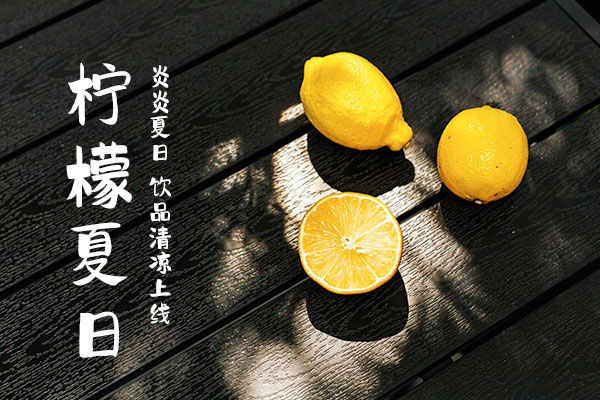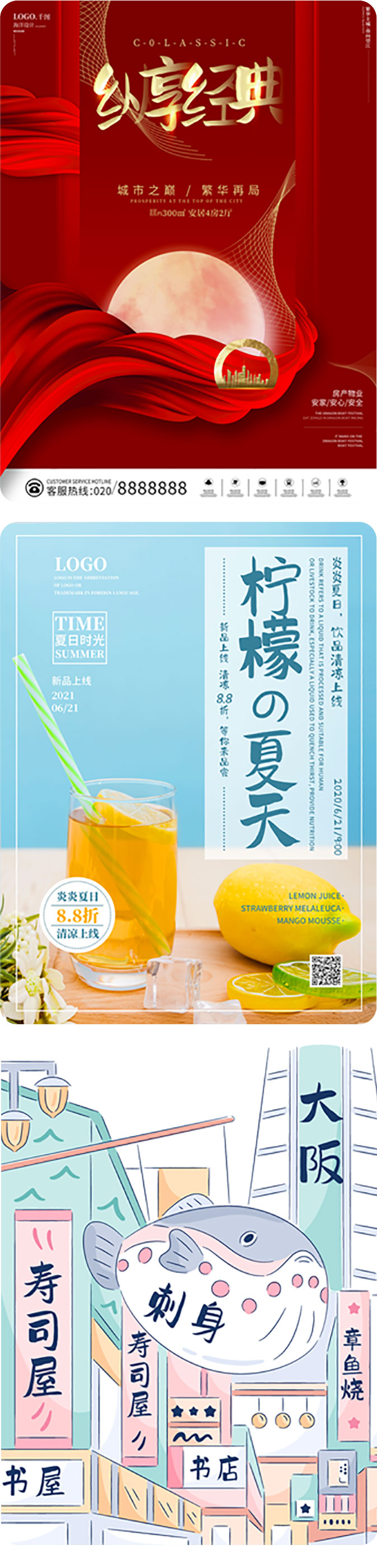
千图马克手写体
千图马克手写体,一款由千图网精心打造的免费商用字体,它的独特风格给人带来一种积极、阳光的感觉。字体设计中,注重笔画的开合度,每个字形之间都保持了恰当的空间,使得文本的排列通透,阅读起来更为轻松、舒适,宛如自由呼吸。
这款字体非常实用,既适合作为标题使用,也可以用于提醒类文字,可以广泛应用于各种场景。无论是在饮品、化妆品、日料、插画等领域,都能发挥出其独特的魅力。
千图马克手写体是由千图网联合国内专业字体设计机构字魂网精心打造的一款公益字体,历时一年多才打磨完成。这款字体包含了西文52个、字母 464个、标点符号451个、数字118个、汉字9394个,非常全面。
千图马克手写体效果预览
千图马克手写体字体效果预览